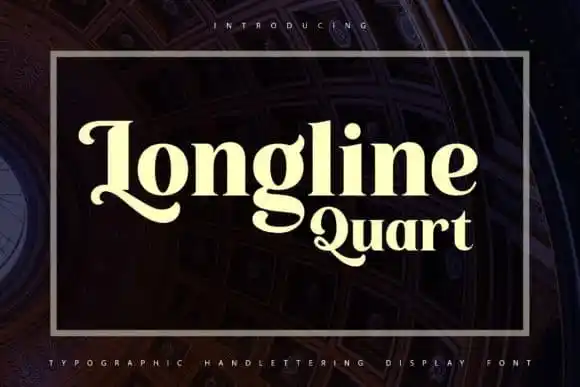
Longline Quartz Serif Font – Download Grátis
A Longline Quartz Serif Font é uma tipografia serif moderna e artística que traz uma pitada de charme e amabilidade para qualquer projeto editorial ou marca. Com sua versatilidade, esta fonte pode ser adaptada para uma ampla variedade de usos. Além disso, o recurso de ligatura permitido por softwares de design avançados permite que você mude rapidamente seu estilo da sofisticada e clássica para artística e criativa, sem precisar gastar tempo ou recursos desnecessários. Adicionar um toque especial a qualquer layout editorial ou logo pode ser simples com essa fonte. Seria uma escolha perfeita para designers buscando uma opção que não é apenas funcional, mas também capaz de agregar estilo e personalidade aos projetos. Engane-se se pensa que ela só é indicada para trabalhos tradicionais; seu design artístico a torna ideal para qualquer projeto moderno ou criativo.